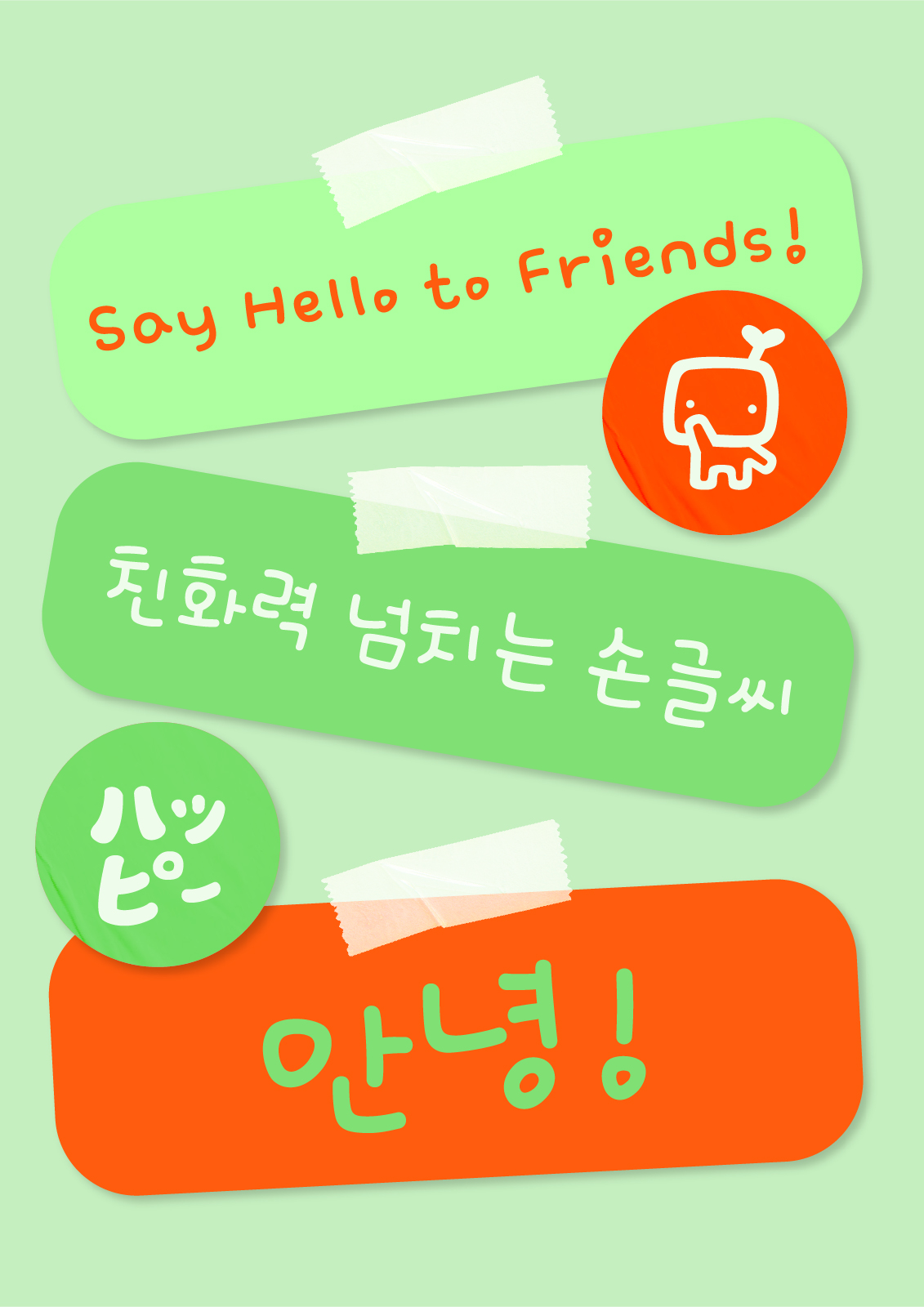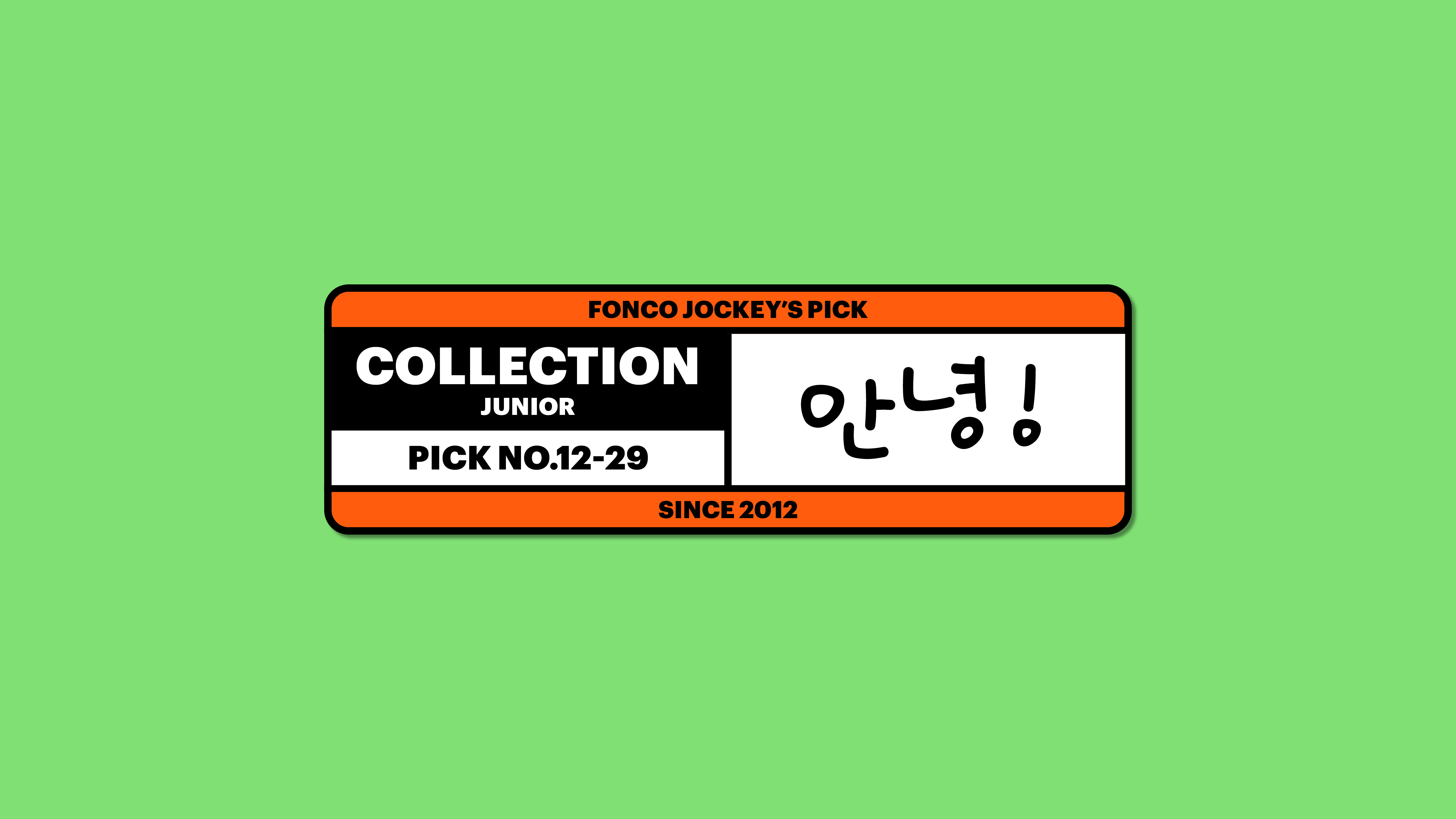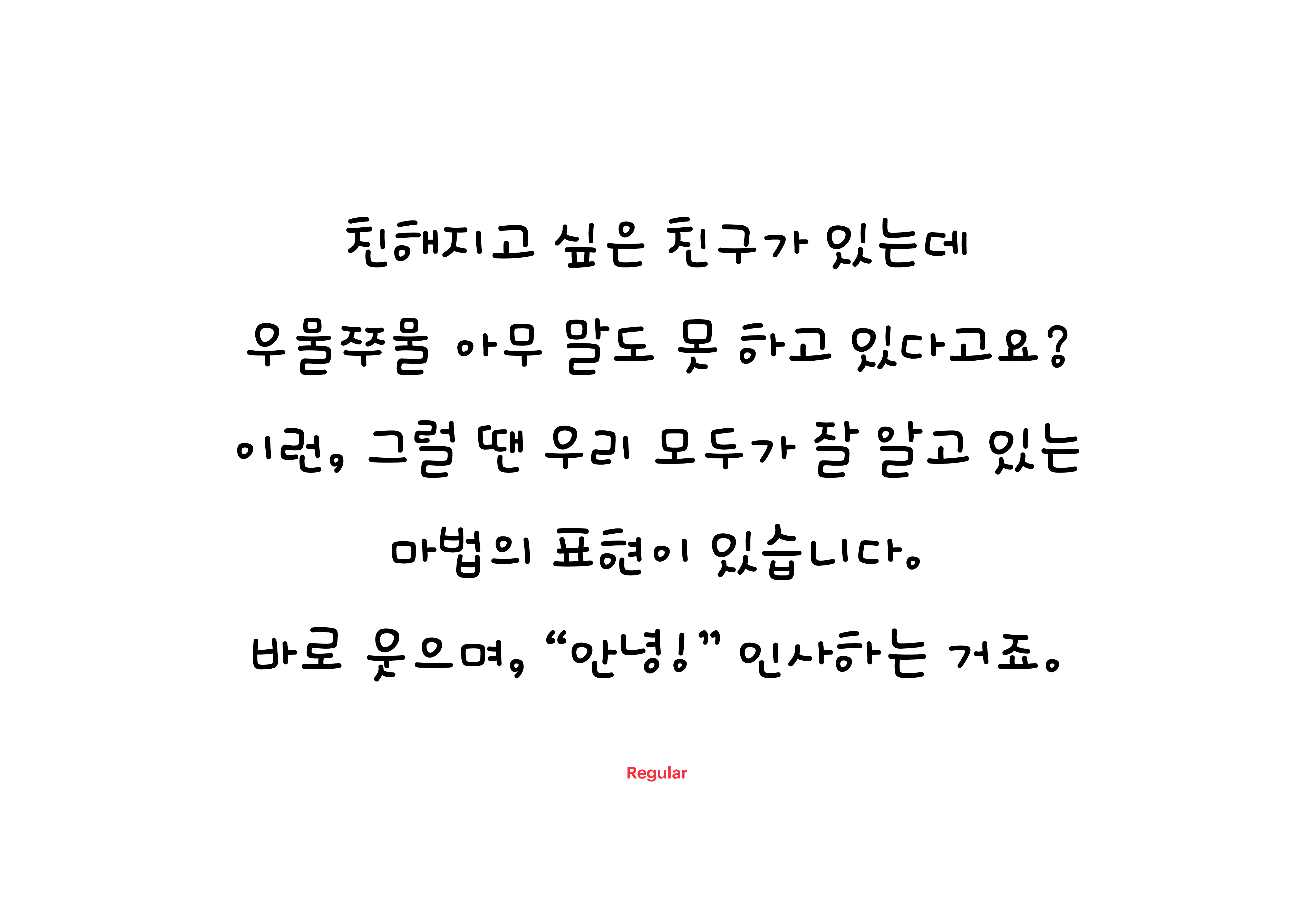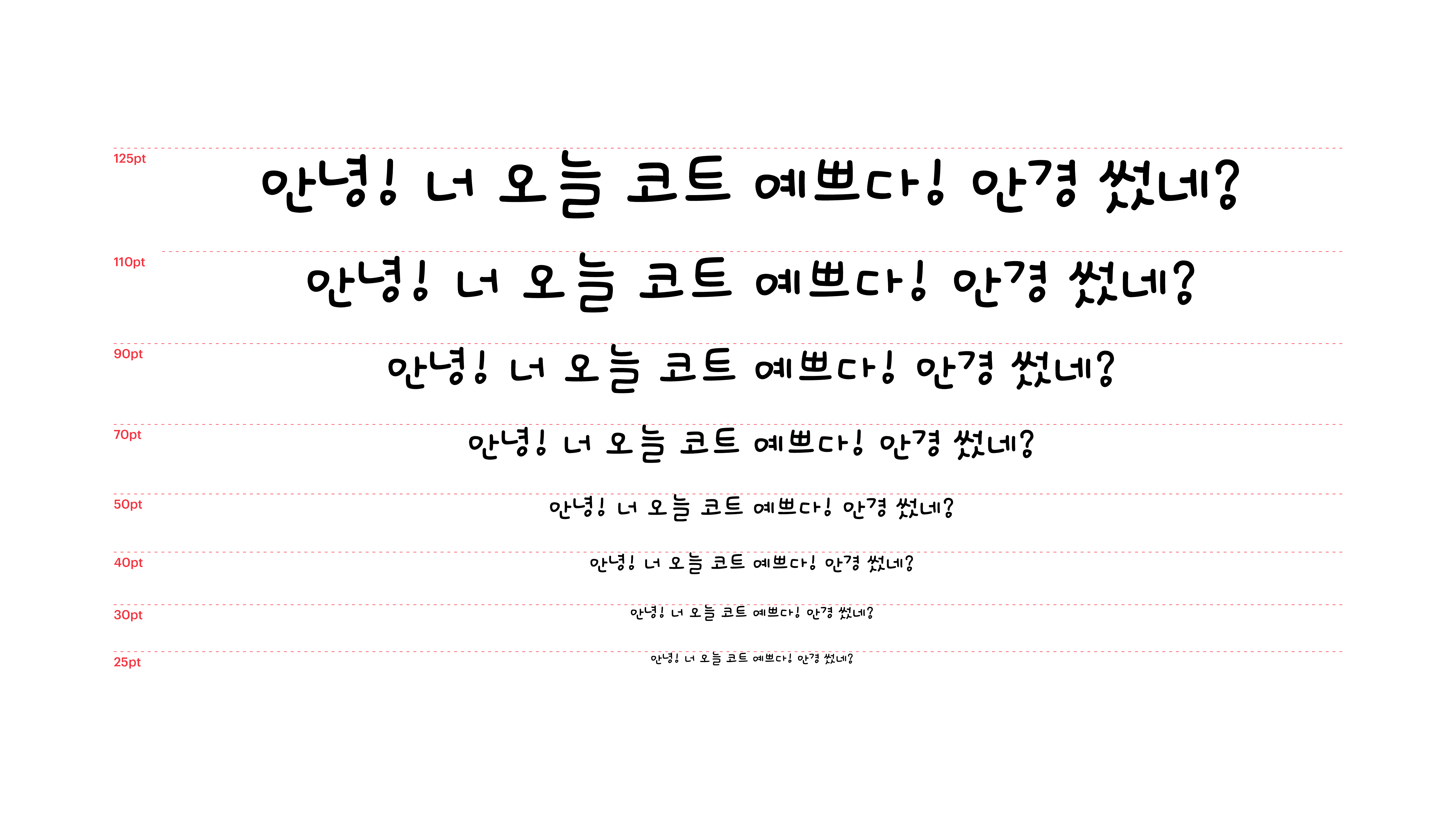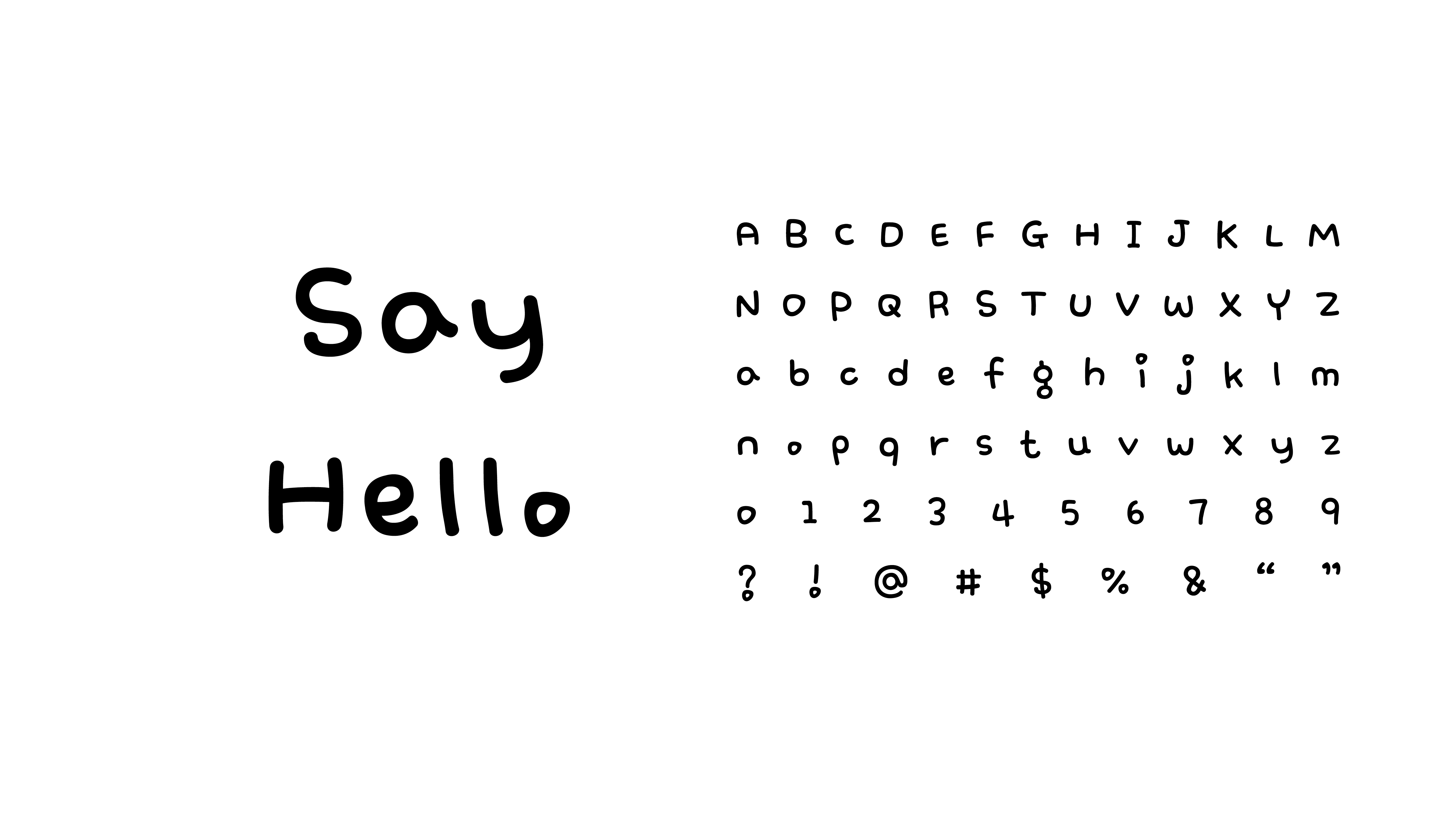
친해지고 싶은 친구가 있는데 우물쭈물 아무 말도 못 하고 있다고요? 이런, 그럴 땐 우리 모두가 잘 알고 있는 마법의 표현이 있습니다. 바로 웃으며, “안녕!” 인사하는 거죠. 이 친화력 넘치는 손글씨 폰트의 표정처럼 반가운 인사를 건네보세요. 안녕! 너 오늘 코트 예쁘다, 안녕? 오늘은 안경 썼네?, 안녕? 근데 우리 끝나고 같이 떡꼬치 사 먹지 않을래? 다들 감 잡으셨죠? 친구가 집으로 돌아가기 전에, 어서요.
Yoon 안녕!